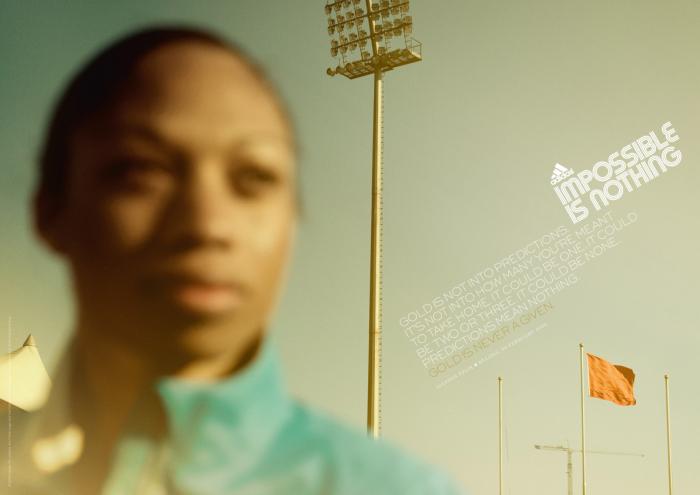
Adidas - Impossible is nothing - Schriftart gesucht
ich bin auf der Suche nach der Adidas Schriftart, die für das "Impossible is nothing" in angehängtem Bild verwendet wurde. Ich habe bereits herausgefunden, dass eine ähnliche Schriftart "Adidas Unity" heißt. Leider ist sie nur ähnlich. Ich muss für die Hochschule allerdings ein Plakat mit genau diesem Font nachbauen.
Danke. Die kommen tatsächlich sehr nah an die Adidas Unity. Leider aber eben auch nicht wirklich an die von mir gesuchte. Das ist auf dem Bild etwas schwer zu sehen, aber wenn man ganz nah ranzoomt, sieht man, dass diese Schriftart ganz feine Streifen hat.
Ich befürchte, dass das eine Eigenentwicklung von Adidas ist. Der Name dazu würde mir vielleicht trotzdem weiterhelfen. Oder, falls jemand eine ähnliche Schriftart kennt?
Danke. Eine Mischung aus Pump Triline und Triselect kommt tatsächlich ziemlich nah.
Falls trotzdem jemand noch die originale Schriftart kennt, gerne posten. :)